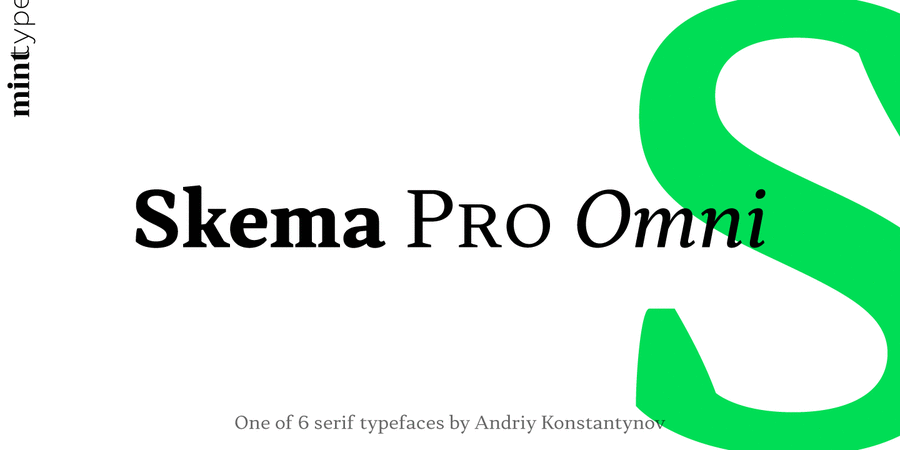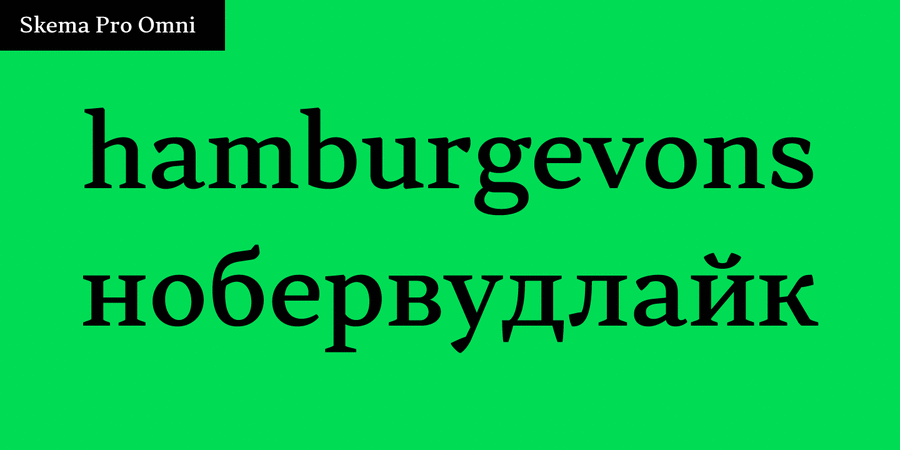
Skema Pro Omni – середньоконтрастна гарнітура з помірною висотою рядкових та слабко нахиленою віссю контрасту. Контрастніша, ніж Skema Pro Text, вона створює довершену, більш формальну текстуру.
Skema Pro – система з 6 антикв, кожна з яких має свій характер і призначення. Разом вони формують величезну супергарнітуру з 84 накреслень для будь-яких можливих завдань.
Сімейство Skema Pro розробив і випустив Андрій Константинов у студії Mint Type у 2017 році.
Асоціації з сімейством шрифтів Skema Pro OmniОсобистість і характер гарнітури:
тонкий, легкий, делікатний, спокійний, рівний, гармонійний, врівноважений, космополітичний, ненав'язливий, технічний, сучасний, точний, логічний, непомітний, культурний, освічений, стійкий, серйозний, твердий, динамічний, худий, якісний, ввічливий, зрозумілий, нейтральний, середній, звичайний, помірний, доступний, комфортний, зручний, гуманітарний, комільфо, благородний, консервативний, традиційний, класичний, архітектурний, тактичний, формальний, універсальний, діловий, практичний, оптимальний, розумний, стабільний, міський, переконливий, пафосний, солідний, авторитетний, відповідальний, значний, суворий, міцний
Місто, література, освіта, культура, бібліотека, мистецтво, музей, проза, архітектура, історія, скульптура, наука, суспільство, юрист, адвокат, фінанси, правосуддя, економіка, бізнес, банк, суд, банкнота, монета Гарнітура має ознаки стилів: